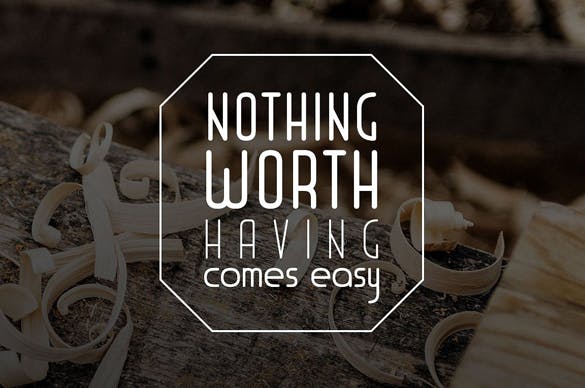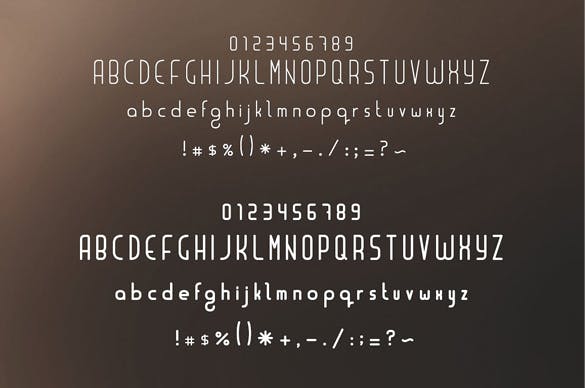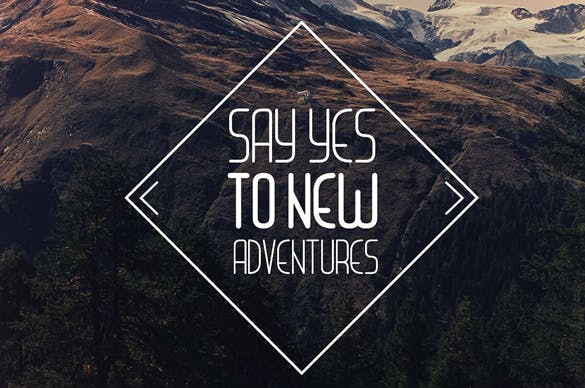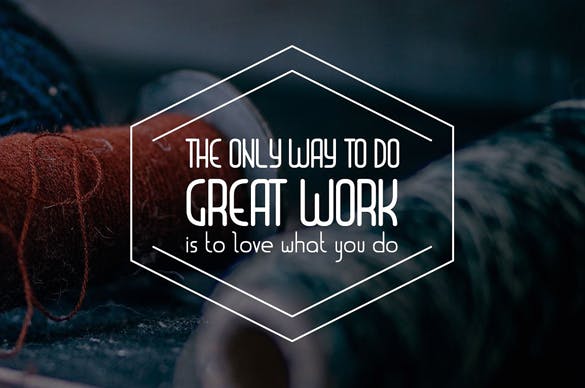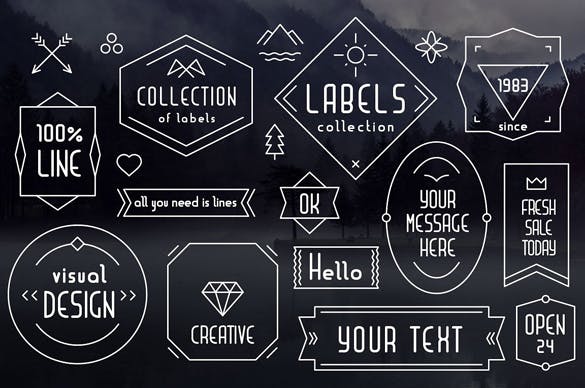
فونت Liner یک فونت بدون سری زیبا است که با لبههای گرد طراحی شده است. این فونت ساده و شیک دارای دو نوع نوشتار است که میتوانند بهصورت ترکیبی استفاده شوند. فونت Liner برای طراحی لوگوها و عناوین کوتاه مناسب است. این فونت با عناصر هنری خطی و فریمها تکمیل شده است تا ایجاد طراحیهای سادهتر را ممکن سازد.